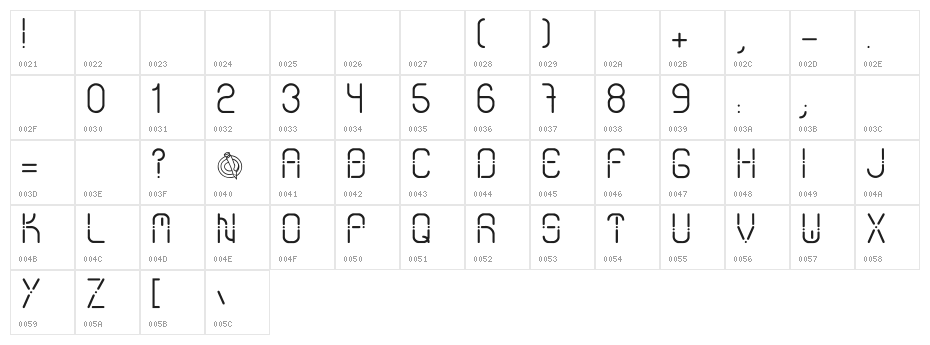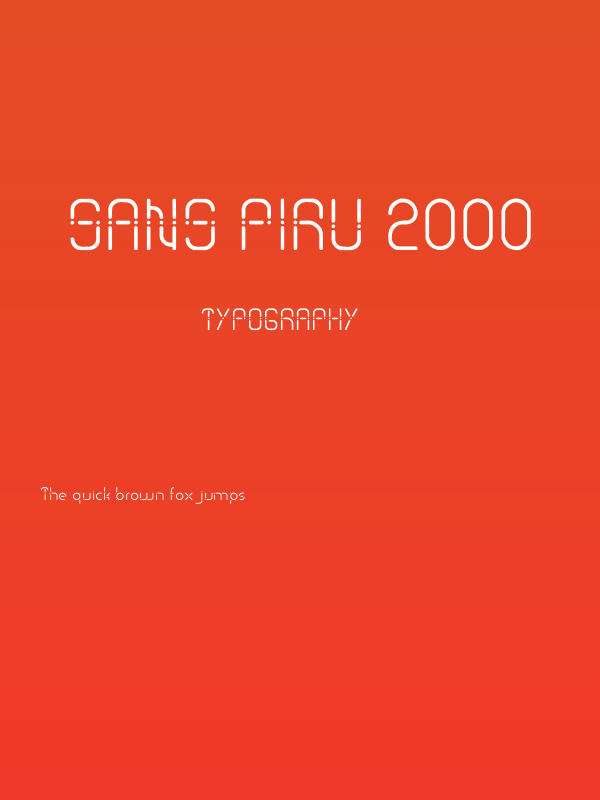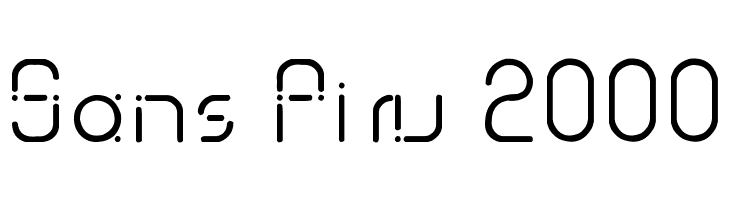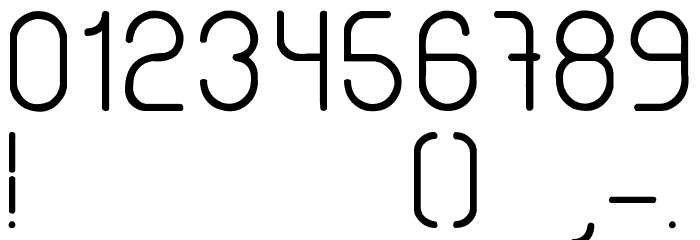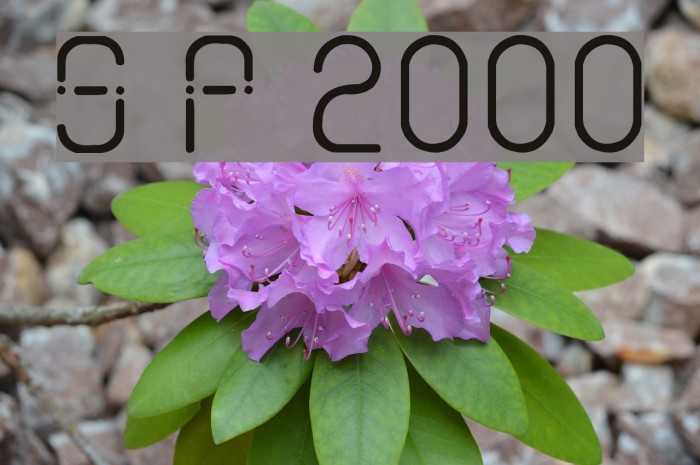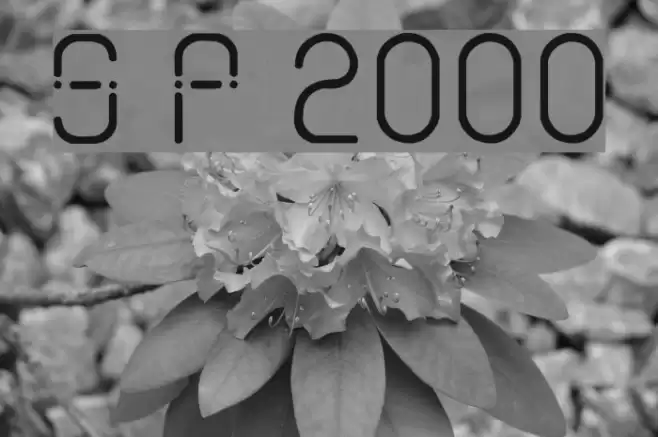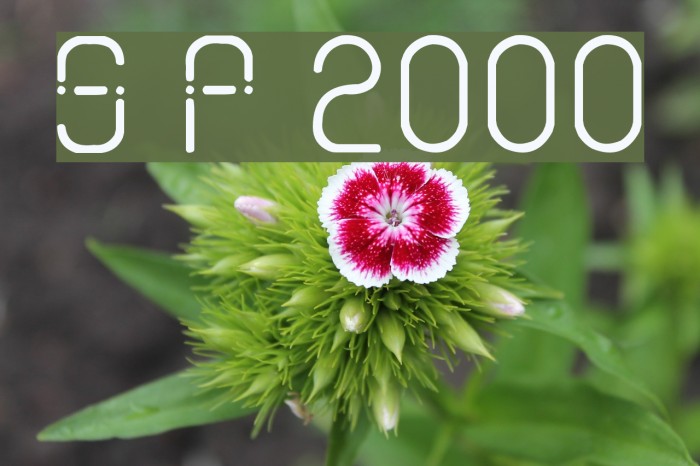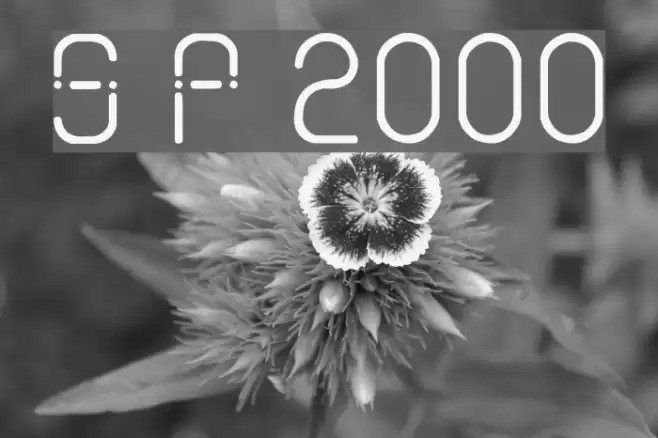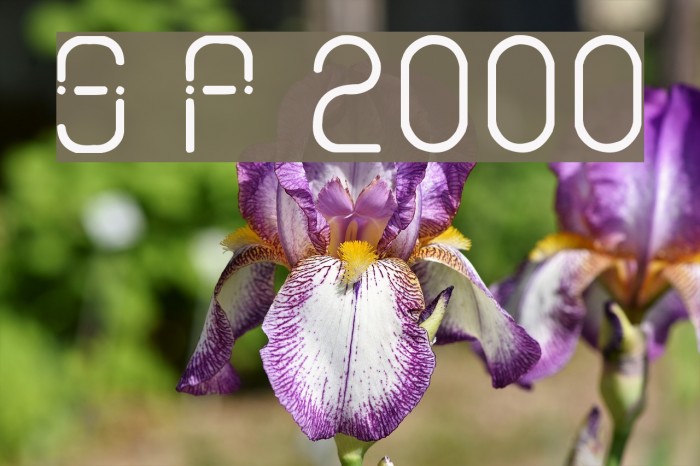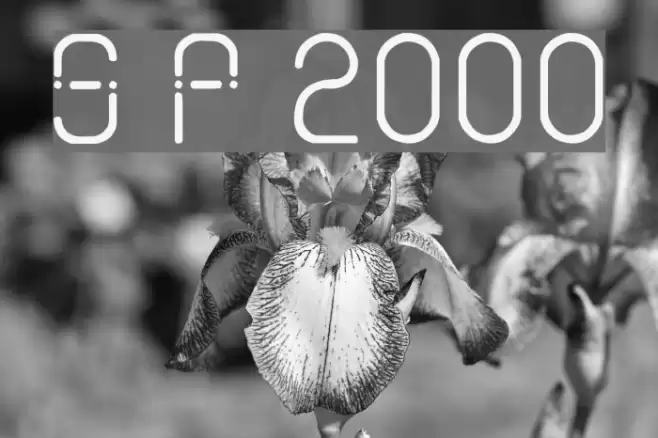
Sans Piru 2000 Font
| Caso d'uso | Logos, Headlines, Digital Interfaces |
| Progetti proposti | Ideal for tech branding, digital interfaces, futuristic posters, and innovative product packaging. |